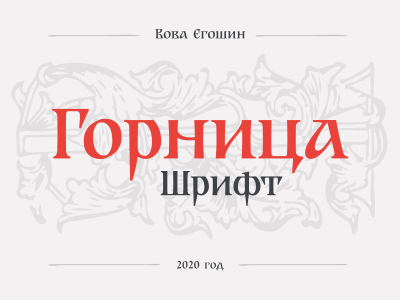
Шрифт Горница
По заказу Петербургского Мельничного Комбината. Hа базе устава, только русская кириллица! Полайкайте, поддержите проект пожалуйста — https://www.behance.net/gallery/109241943/Gornitsa-typeface